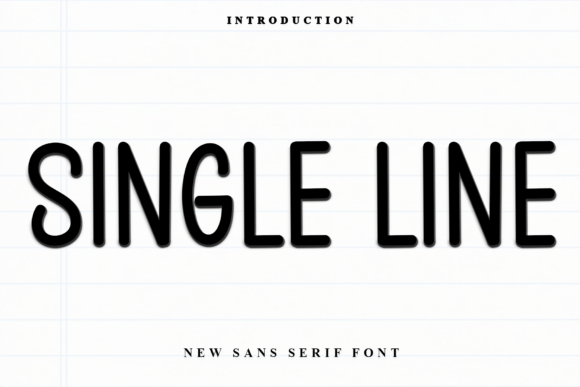
Single Line
Si buscas recursos de alta calidad como Single Line, este paquete premium es una opción fantástica para tus proyectos creativos.
Elaborado con precisión, Single Line proporciona vectores limpios, tipografía suave y una licencia comercial para tu tranquilidad.
Ya sea que estés creando productos POD (impresión bajo demanda), invitaciones de boda o gráficos para redes sociales, Single Line es una opción ideal.